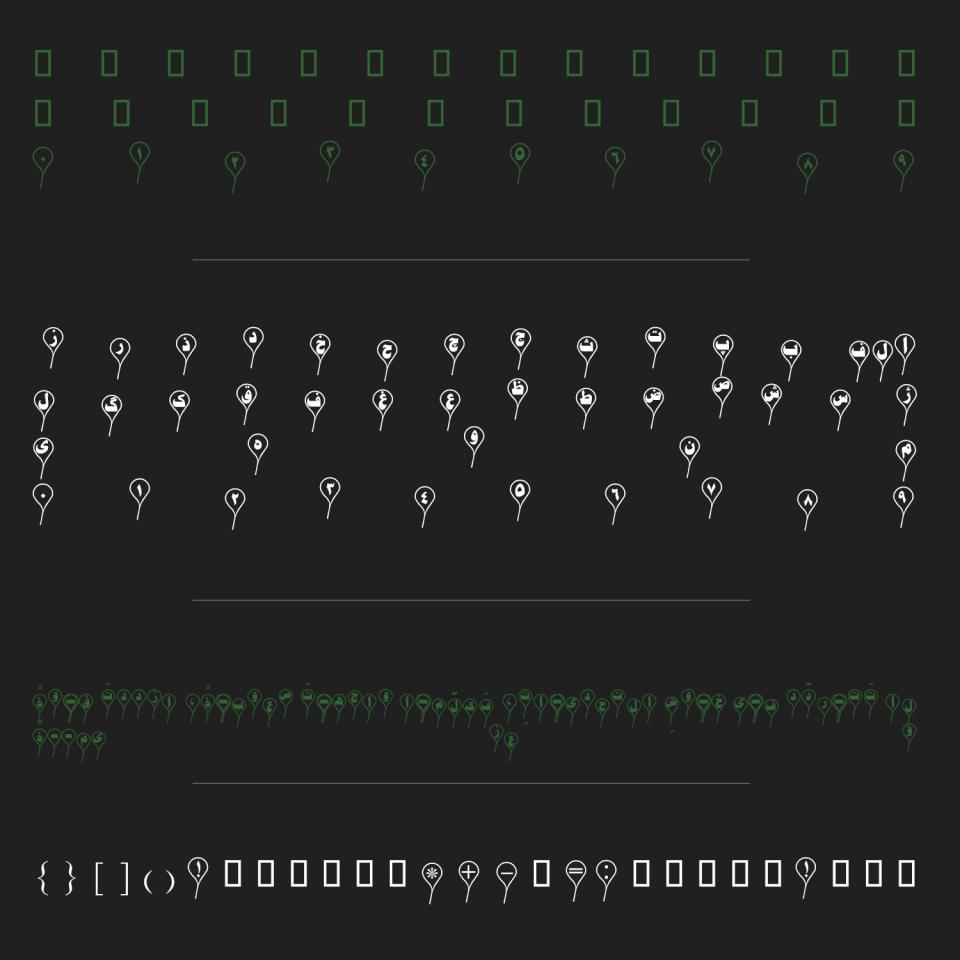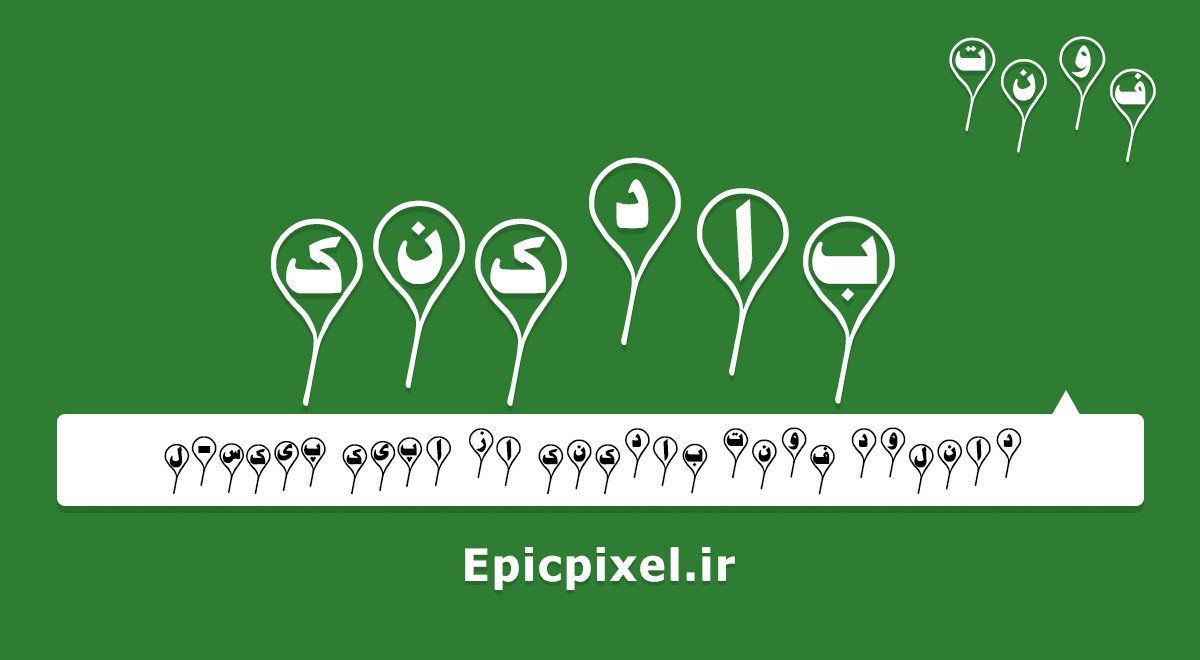
2 فونت بادکنک فارسی Badkonak
فونت بادکنک فارسی، با ظاهر فانتزی و دوست داشتنی اش، انتخابی ایده آل برای پروژه هایی است که نیاز به حسی شاد، کودکانه و غیررسمی دارند. این فونت با خطوط نرم و گرد خود، حسی از سبکی و بازیگوشی را القا می کند و به همین دلیل برای طراحی هایی مانند کارت های تبریک، پوسترها و بنرهای تبلیغاتی مرتبط با کودکان، بسته بندی محصولات و حتی طراحی وب سایت هایی با حال و هوای شاد و دوستانه بسیار مناسب است.
یکی از ویژگی های برجسته فونت بادکنک، خوانایی بالای آن در اندازه های مختلف است. این یعنی چه در متن های کوتاه و چه در پاراگراف های بلند، چشم مخاطب به راحتی می تواند حروف را دنبال کند و متن را بخواند. البته، به دلیل شکل خاص حروف، شاید برای متن های طولانی و رسمی، انتخاب ایده آلی نباشد و بهتر است در جاهایی استفاده شود که هدف، جلب توجه و ایجاد حس خوب است، نه انتقال حجم زیادی از اطلاعات به شکلی کاملا رسمی.
در نهایت، فونت بادکنک فارسی با ظاهر منحصربه فردش، می تواند به طرح های شما شخصیتی خاص ببخشد و آن ها را از سایر طرح ها متمایز کند. اگر به دنبال فونتی هستید که هم زیبا باشد، هم خوانا و هم رایگان، فونت بادکنک فارسی می تواند گزینه ی بسیار خوبی برای شما باشد.